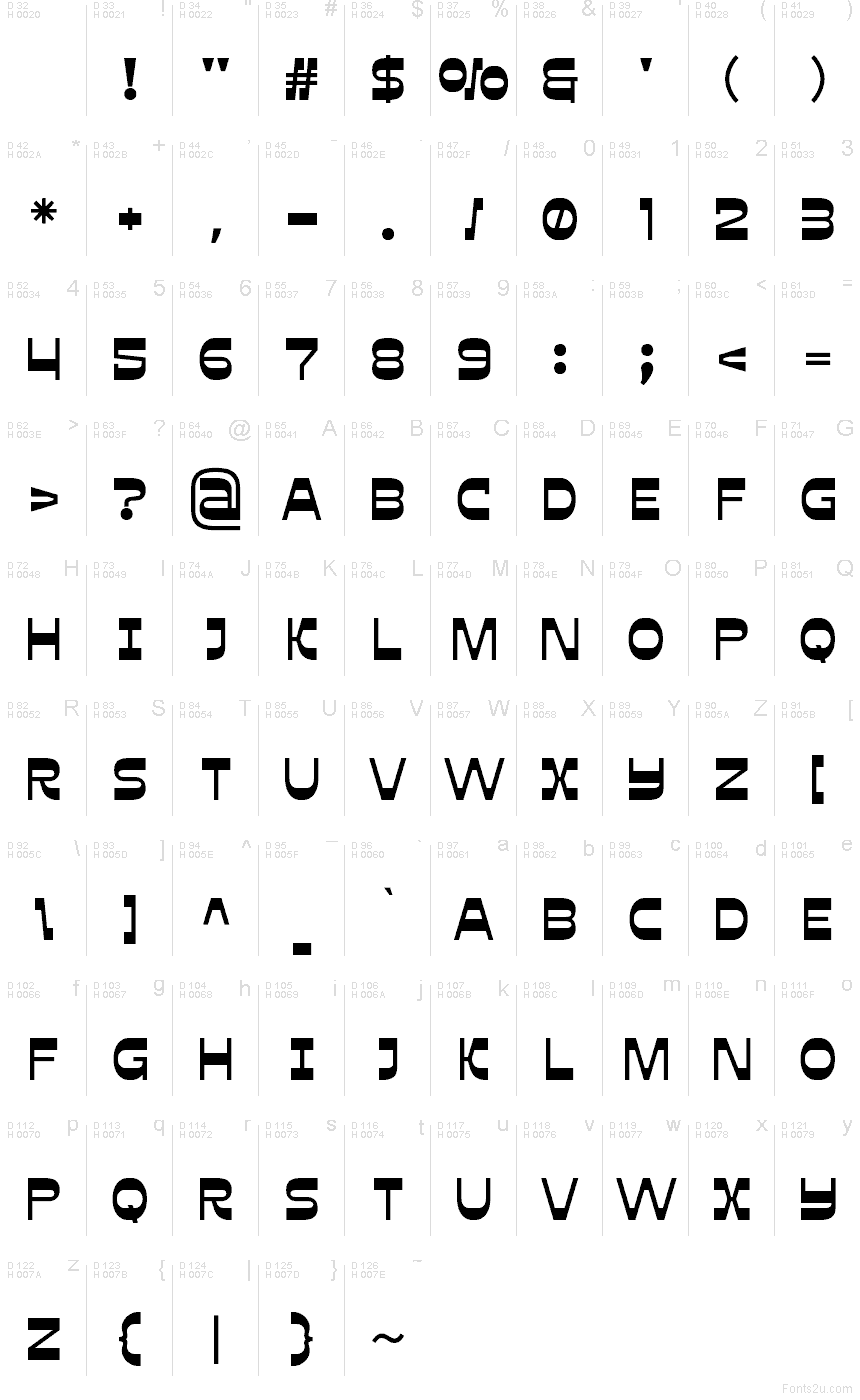
خط Cherry Pop من Linecreative هو خط عرض هندسي رجعي مجاني، مبني من ضربات عريضة وصلبة وأشكال نمطية مدمجة. تجمع حروفه الكبيرة الظاهرة بين مساحات داخلية مربعة ومنحنيات خارجية مستديرة، مما يمنحه مظهراً قوياً مستوحى من الخيال العلمي في سبعينيات القرن العشرين.
تتداعى أشكاله لتشبه لوحات الأجهزة ورسومات خزائن ألعاب الآركيد. هذا الارتباط يجعله خياراً مقنعاً للعلامات التجارية لألعاب الفيديو، وفن الملصقات، والمنتجات الموسيقية، وتغليف المنتجات الترفيهية الموجهة لعشاق التصميم المستقبلي الرجعي والحنين إلى الماضي الإلكتروني.
Cherry Pop